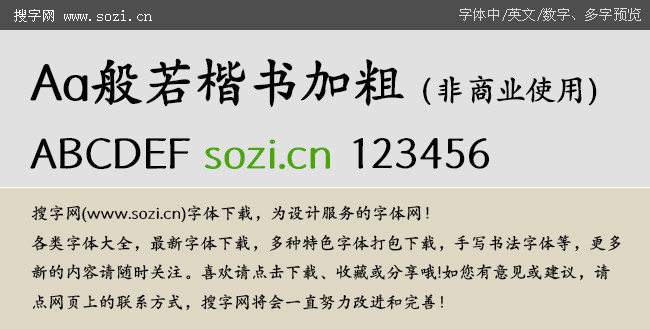
Aa般若楷書加粗
搜字網(wǎng)給大家提供一款A(yù)a般若楷書加粗(非商業(yè)使用)中文字體下載,該字體是一款中文楷體字體,字體筆觸較為粗實(shí),簡潔大方,字形端正大氣。適合書裝設(shè)計、包裝設(shè)計、海報設(shè)計等應(yīng)用(此字體為個人非商用版,商用可以聯(lián)系QQ:1006760504)。